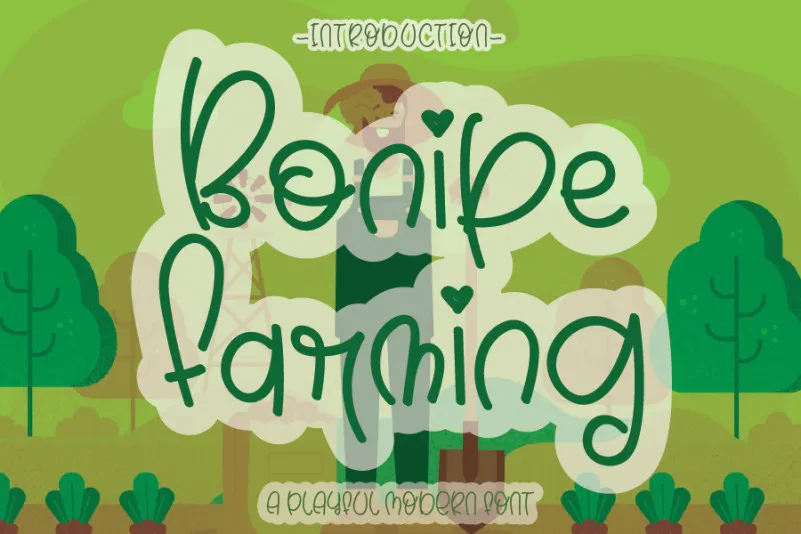
Bonipe Farming Font – Download Grátis
A Bonipe Farming Font é uma fonte escrita à mão que oferece grande flexibilidade para designers criativos. Ela é perfeitamente adaptável a várias aplicações, desde títulos a textos de texto interno, tornando-se um recurso valioso em qualquer projeto. Essencialmente, ela é um traço de letra à mão delicado, quirk e animado, capaz de dar vida aos seus projetos. Além disso, oferece uma vasta variedade de estilos que podem ser usados para criar trabalhos artísticos únicos e variados. Como a designer handwrittenwanda o descreveu, esta font será um grande amigo durante os momentos em que você precisa transformar suas ideias num trabalho realista e criativo. Por isso, ela é perfeita para quem deseja explorar novos estilos sem medo de experimentar diferentes formas. Experimente a Bonipe Farming Font e encontre o design ideal para seus projetos!